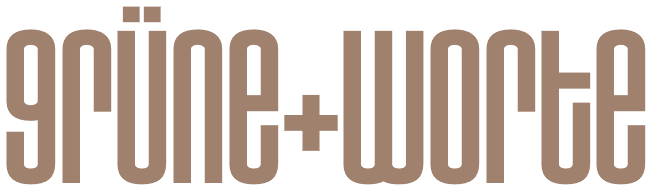
weiß jemand, um welchen Font es sich hier handelt? Whatthefont hat mir nicht weitergeholfen.
Wenn Du bei MyFonts »unicase« als Suchfilter eingibst, dann kommen eine ganze Menge Schriften zur Auswahl, zum Beispiel die
die schon ziemlich dicht dran ist. Ich bin jetzt nicht alle Ergebnisse durchgegangen, aber vielleicht wirst Du dort fündig?